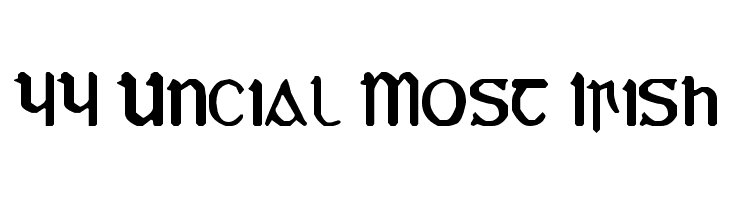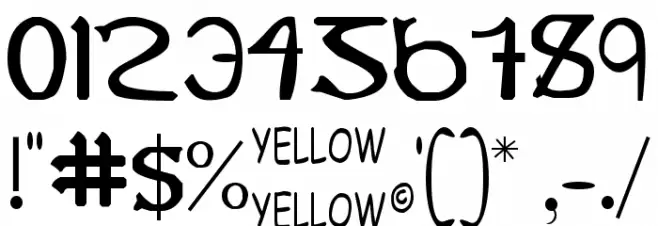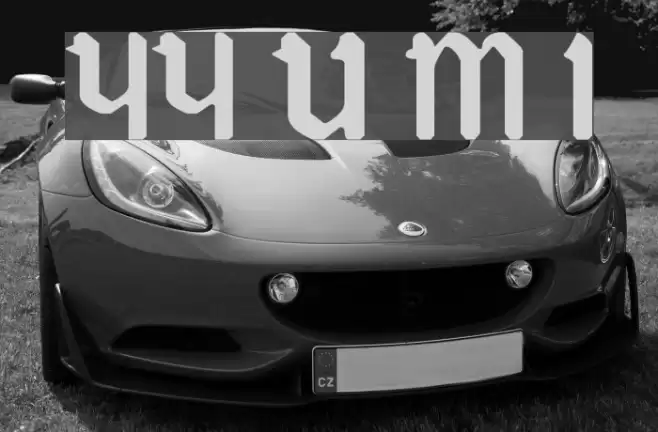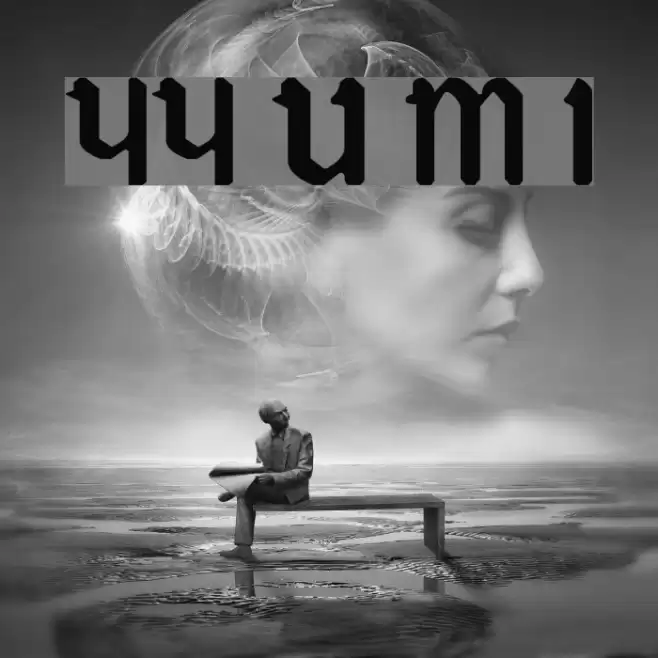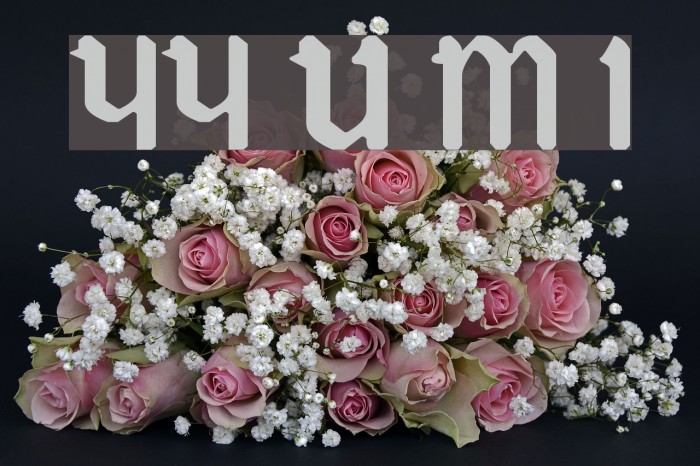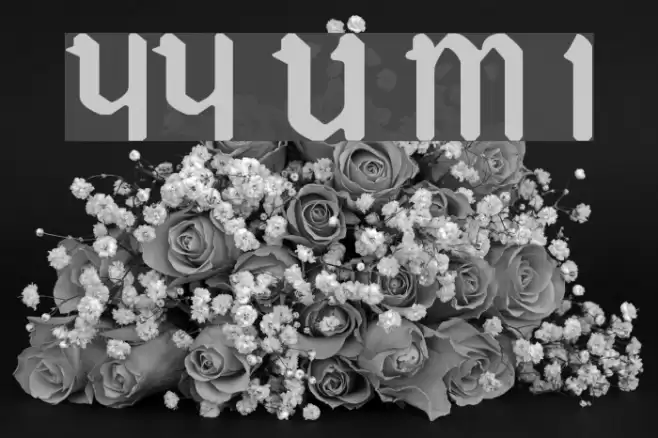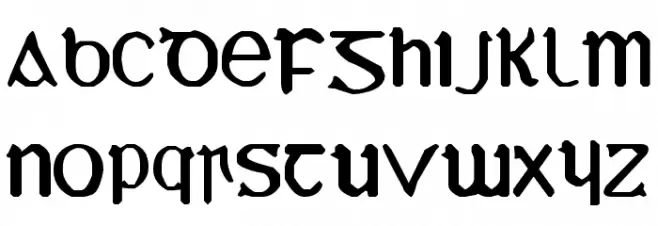
YY Uncial Most Irish Font
| Proiecte propuse | Ideal for historical documents, themed event invitations, book covers, and branding that seeks a vintage or Celtic aesthetic. |